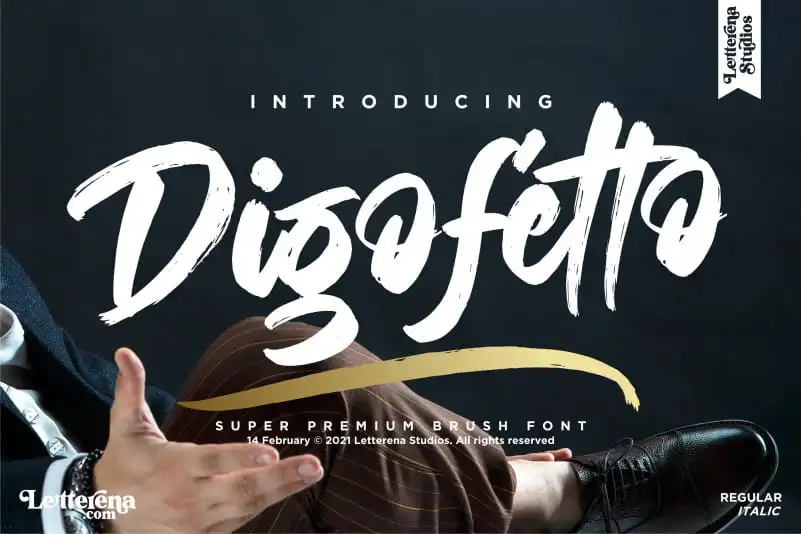
A Digofetto Brush Font é uma escolha perfeita para projetos que exigem um toque de destaque e elegância. Projetada pela Letterenastudios, essa fonte de traço áspero se destaca por sua força e modernidade, tornando-a ideal não apenas para logos e marcas inovadoras, mas também para aplicativos como embalagens de produtos, revistas e capas de livros. Suas linhas robustas e atraentes são perfeitas para criar um estilo sóbrio em designs digitais ou impressos, criando uma aparência que chama a atenção instantaneamente. A Digofetto Brush Font é uma ferramenta poderosa para designers gráficos que desejam trazer a sua visão ao design de forma elegante e respeitável. Perfecto para qualquer projeto que precise de um toque brilhante, seja ele em mugs, cartões de visita ou até mesmo em selos de foto, essa fonte é definitivamente uma adição valiosa à coleção dos criadores.